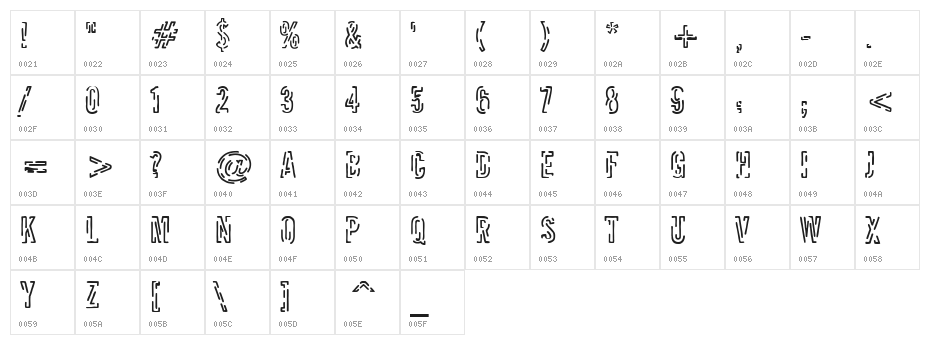
Packet Font
✎ Outline
| Gesamtstil | Modern, Industrial |
| Vorgeschlagene Projekte | Ideal for branding, posters, signage, and any design requiring a bold, industrial aesthetic. |